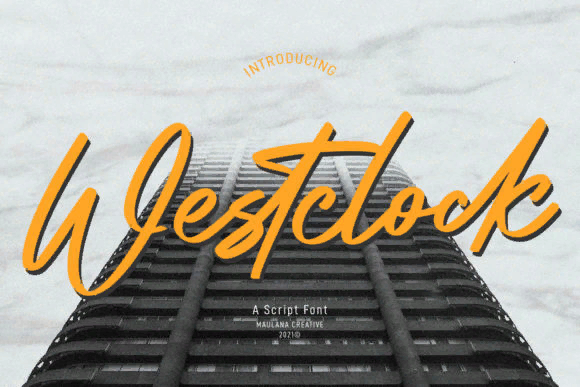
Название: Westclock Script Font (2021)
Westclock - это шикарный, плавный шрифт, излучающий изысканность и элегантность.
Стильные чередования и лигатуры делают этот шрифт идеальным для любого проекта.